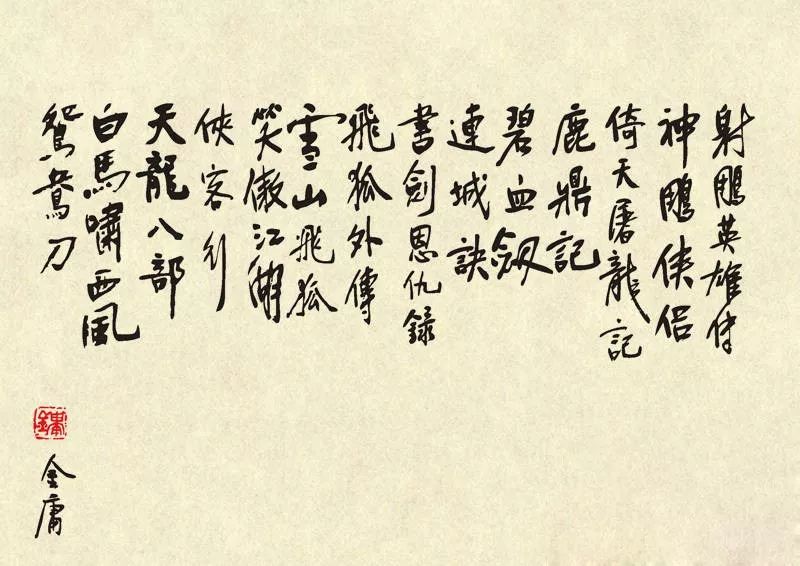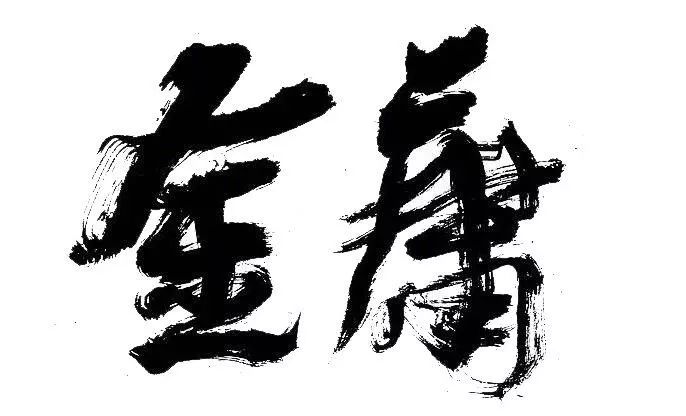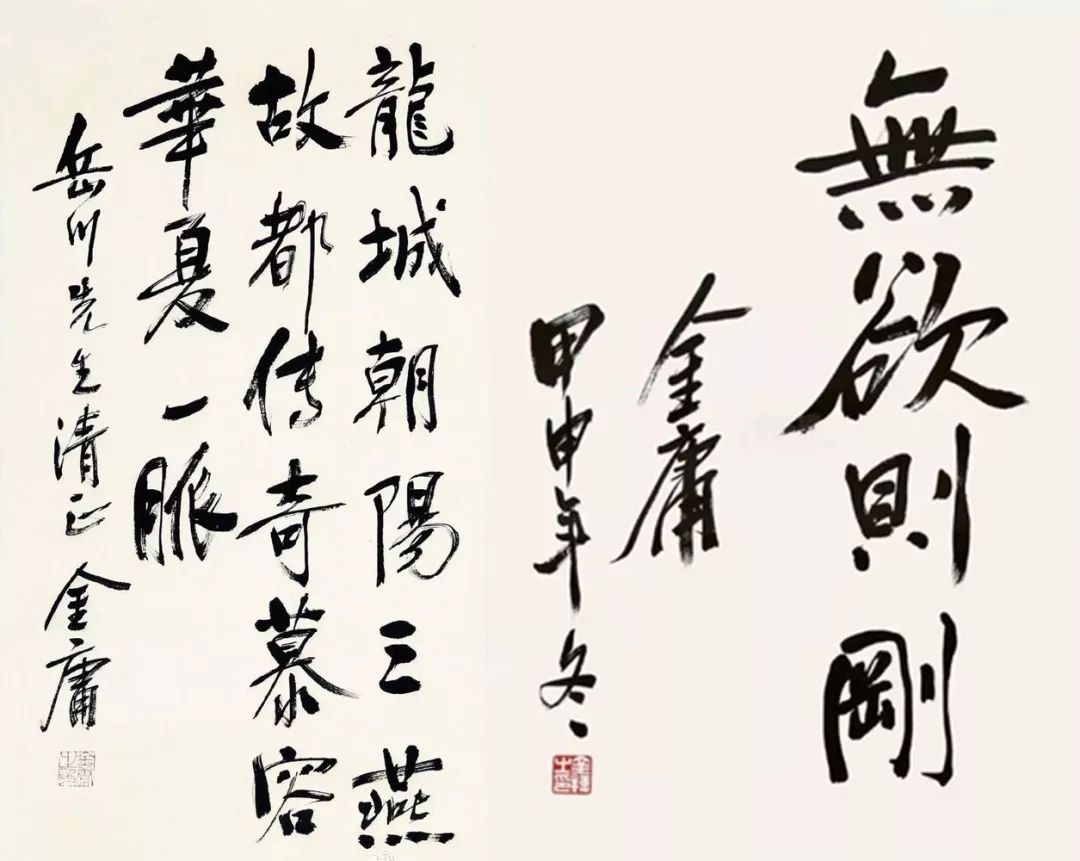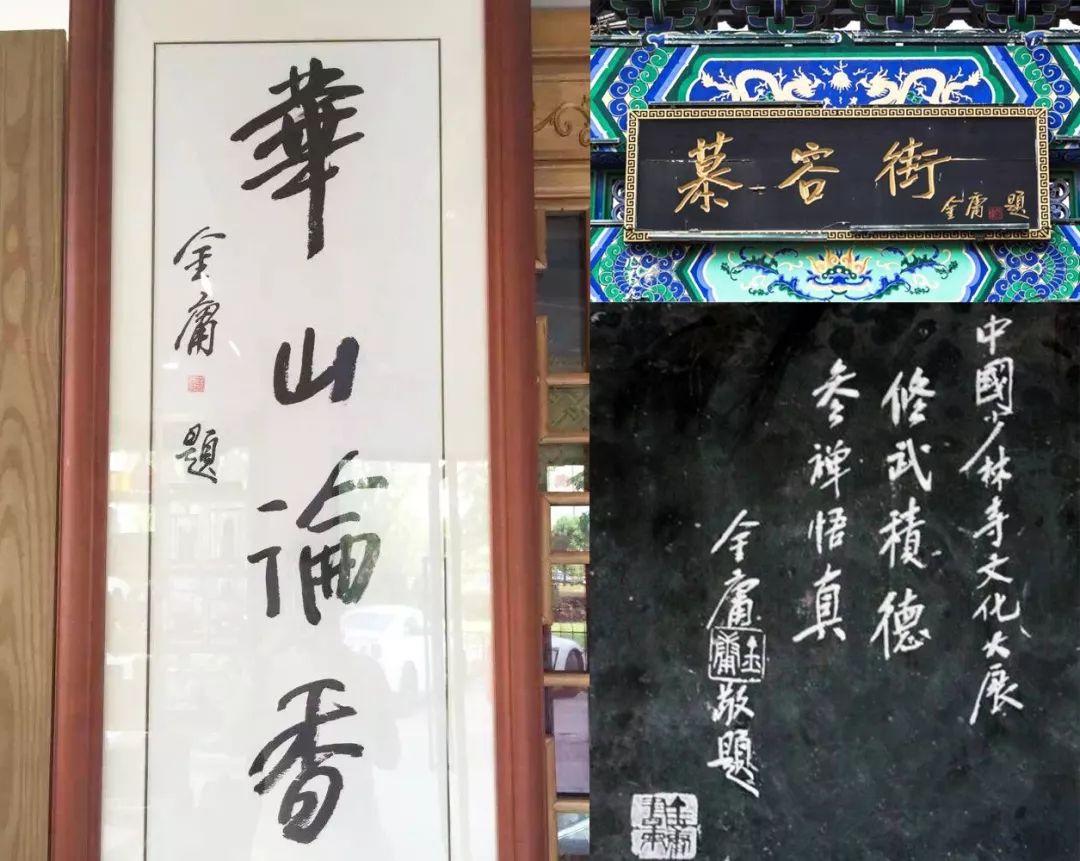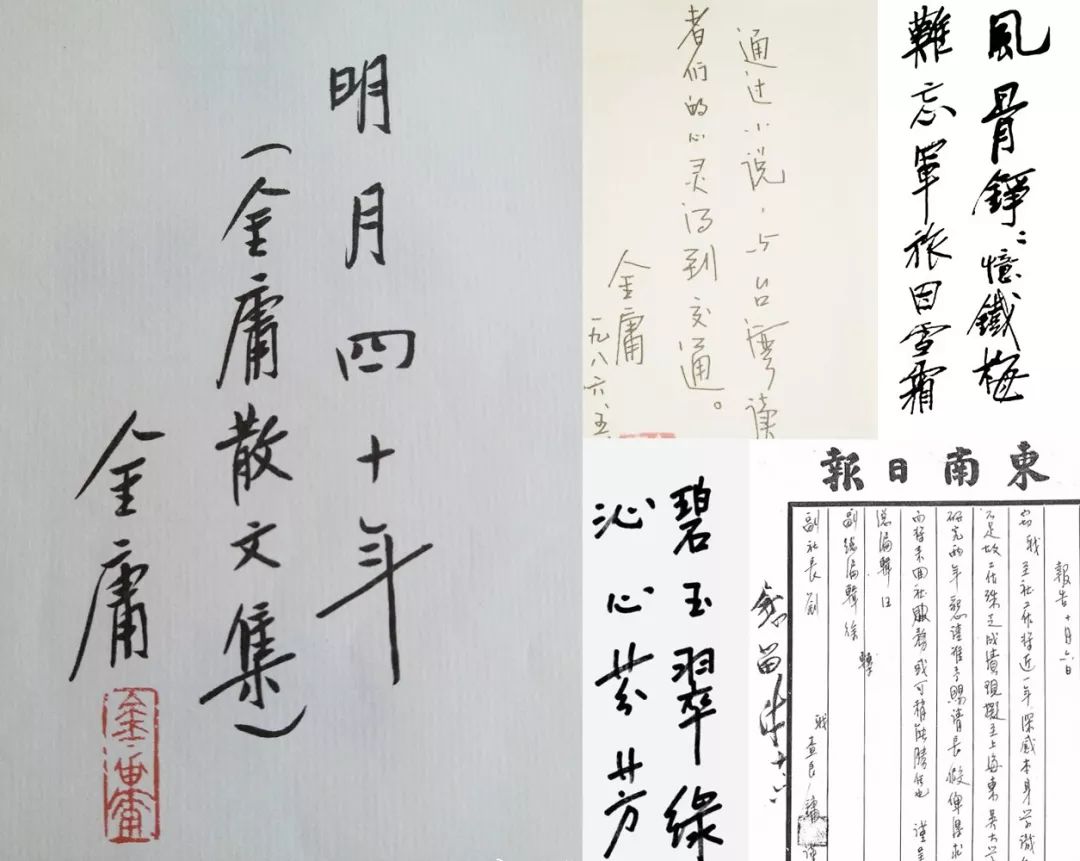
金庸“归隐”,可他的书法江湖还在流传
{{tag.name}}昨晚听闻金庸离世,柚子感觉内心无比空虚,虽然没见过他,他更不认识我,但总觉得冥冥之中,彼此承载了共同的记忆。
他创作的杨过、张无忌、小龙女、韦小宝……真是影响了一代又一代的人,所以94岁的他离世,我更觉得是一种“归隐”,去到另一个江湖而已,但他的小说、书法,从未在我们的心中离开。
他的小说之所以经典,有很重要的一个原因,就是将书法融入了武侠江湖,之前在年少时不懂周杰伦的忍者,长大了才明白它的终极奥义也说过,书道和忍者就是你中有我,我中有你,同为修身之道。
所以你在《倚天屠龙记》中看到张翠山用“银钩铁划”,写下“武林至尊,宝刀屠龙,号令天下,莫敢不从,倚天不出,谁与争锋”,折服了金毛狮王谢逊。
在《神雕侠侣》中看到朱子柳,用真草隶篆“一阳书指”,大战蒙古王子霍都。
还有《笑傲江湖》中的秃笔翁……
他们都是以笔代剑的书法高手,在金庸的笔下惊人夺目。
不过金庸自身的“墨宝”也是剑道侠骨,十分硬朗,一点都看不出是高龄的人写的,看看他的“小说体”:
在其他的书法作品中,也能看出其字势。用笔很潇洒,字体棱角突出,中宫收紧,落笔铿锵有力,一笔一划,都似乎蕴藏着一套极高明的剑术。
不光是纸面上的,在很多地方,你都能看到金庸的题字。
有人说金庸的书法“魏碑”味很浓,走的是传统路线,那再来看看硬笔字,是不是集硬朗与情怀于一身。
可惜大师没出一款字体,不然我们就能时时刻刻缅怀他了,不过柚子也找到一些有武侠气息的书法字体,借助经典语录,再次重温金庸吧!(前方高能,请准备好纸巾)。
▲汉仪秦川飞影
▲汉仪许静行楷
▲逐浪报人书法行体
▲汉仪新蒂赵孟頫体
▲汉仪尚巍手书
▲汉仪张乃仁行书
▲汉仪程行简
▲汉仪合龙行书
▲汉仪雪君体简
最后我想说,金大侠,放心,
你的江湖一直有我们在!